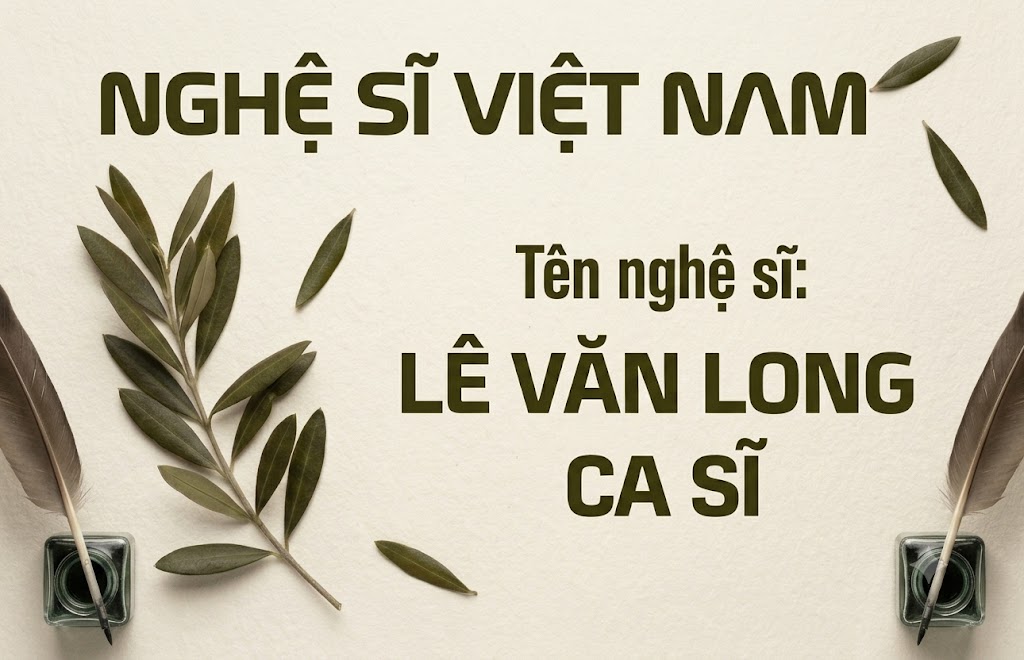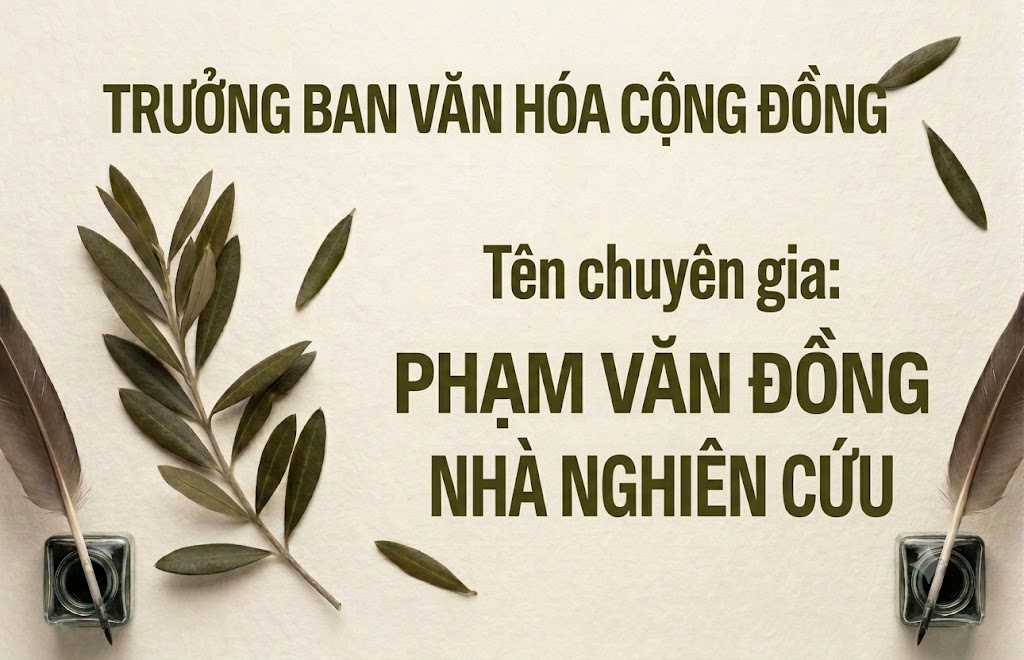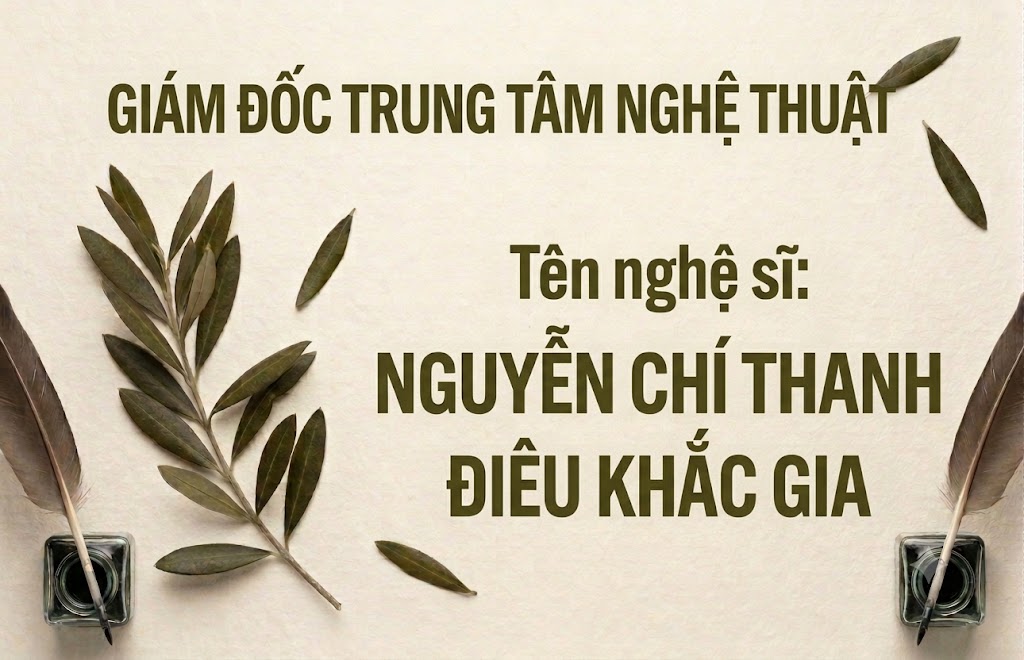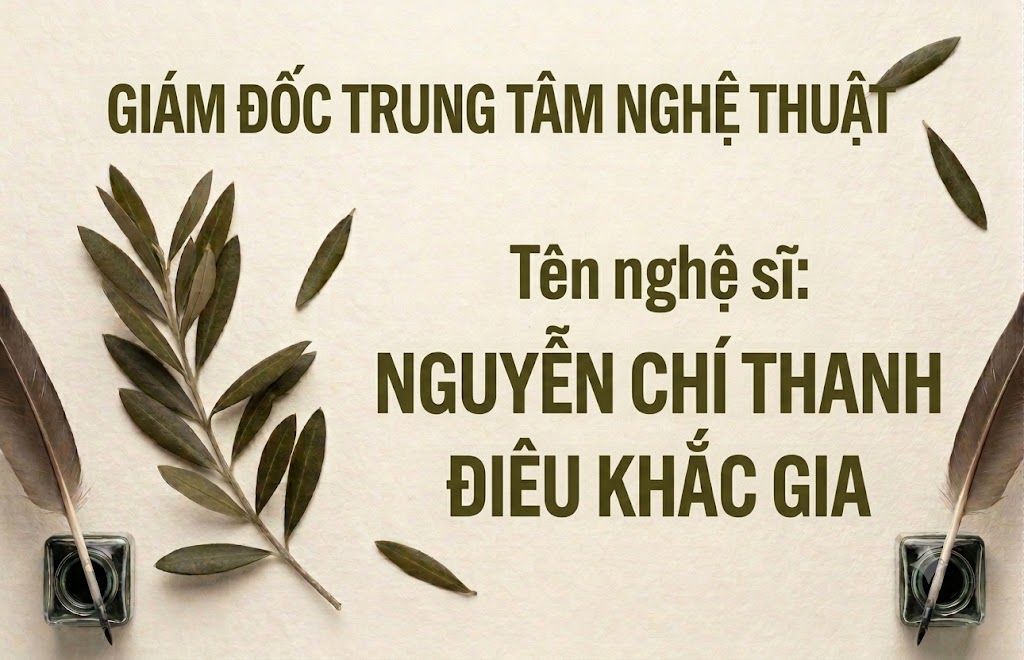
1FTV Nasi
Trong các xu hướng thiết kế đồ họa truyền thông hiện nay, việc sử dụng các phông chữ hình khối bo góc đang ngày càng được ưa chuộng rộng rãi.
Kiểu chữ này mang lại cảm giác vừa chắc chắn, hiện đại lại vừa thân thiện, không bị quá thô cứng như các dòng font vuông vắn thông thường.
Nếu bạn đang muốn tìm kiếm một giải pháp thiết kế làm tiêu đề video ngắn, banner quảng cáo hay ảnh thu nhỏ cá tính, thì font 1FTV Nasi chính là sự lựa chọn hoàn hảo.
Giới thiệu về font 1FTV Nasi
Font 1FTV Nasi là một bộ chữ display không chân phối hợp hoàn hảo giữa phong cách geometric hình học và những đường bo cong mềm mại.
Bộ font này được tối ưu hóa đồng bộ ở phiên bản 1.000, mang lại kết cấu đường nét vô cùng gọn gàng và tinh tế cho từng chữ cái.
Được thực hiện và chia sẻ rộng rãi bởi đội ngũ 1FTV, đây là giải pháp thiết kế tuyệt vời cho những ai đang tìm kiếm sự phá cách độc đáo tại Việt Nam.
Đặc điểm nổi bật của phong cách thiết kế Nasi
Sức hút lớn nhất của font 1FTV Nasi đến từ cấu trúc phom chữ vuông vắn nhưng các góc ngoài lại được bo tròn nhẹ nhàng một cách tinh tế.
Sự kết hợp này tạo ra một tổng thể thị giác vừa vững chãi, kiên cố như khối hộp, vừa mang nét mộc mạc, gần gũi và đầy tính sáng tạo.
Phông chữ được xây dựng theo định dạng all-caps viết hoa đồng bộ cho cả hai hệ thống ký tự, giúp tiêu đề luôn có sự cân bằng tuyệt đối về mặt cao độ.
Độ dày nét chữ thuộc nhóm bold vừa phải, kết hợp với các khoảng hở counter bên trong rộng rãi, giúp văn bản luôn rõ ràng và cực kỳ dễ đọc từ khoảng cách xa.
Để phông chữ vận hành mượt mà trên mọi hệ thống máy tính, phiên bản font 1FTV Nasi đã trải qua quy trình xử lý thông số kỹ thuật vô cùng kỹ lưỡng.
Hệ thống khoảng cách chữ và độ giãn dòng đã được căn chỉnh chuẩn xác, giúp các từ khi đứng cạnh nhau luôn giữ được sự liền mạch và thẩm mỹ tốt nhất.
Bên cạnh hệ thống chữ cái viết hoa đồng bộ, phông chữ còn tích hợp đầy đủ dãy số từ 0-9 cùng hệ thống các ký tự đặc biệt, dấu câu thông dụng (1234567890.:,;'"(!?)+-*/=).
Tiện ích này giúp bạn thoải mái sáng tạo các nội dung quảng cáo hay biên tập video tiếng Việt mà không lo gặp phải tình trạng lỗi hiển thị hay bị thiếu ký tự khi gõ.
Hình ảnh demo thực tế của font 1FTV Nasi
Để giúp bạn dễ dàng hình dung khả năng co giãn và hiển thị linh hoạt của phông chữ này trên các kích thước khác nhau, hãy cùng xem qua bảng mô phỏng thực tế:
Kích thước nhỏ (12pt – 24pt): Các nét chữ hình khối và dấu tiếng Việt vẫn hiển thị rõ ràng, ngay ngắn, cực kỳ dễ đọc trên màn hình điện thoại di động.
Kích thước lớn (36pt – 72pt): Đây là không gian lý tưởng để font chữ phô diễn toàn bộ sự chuyên nghiệp, tạo hiệu ứng thị giác gọn gàng cho các tiêu đề chính.
Ứng dụng của font Nasi trong thiết kế đồ họa và làm video
Sở hữu nét cá tính tối giản và cấu trúc hình học linh hoạt, font 1FTV Nasi mở ra không gian ứng dụng rộng lớn cho các dự án truyền thông:
Thiết kế thumbnail Youtube và ảnh thu nhỏ mạng xã hội: Đây là vũ khí tuyệt vời cho các video thuộc chủ đề đời sống, review ẩm thực, chia sẻ kiến thức hoặc các nội dung giải trí của giới trẻ.
Làm tiêu đề video ngắn (Tiktok, Shorts, Reels): Cấu trúc chữ độc lạ này giúp các câu từ khóa chính hay tiêu đề mở đầu video trở nên vô cùng bắt mắt và giữ chân người xem lướt chậm lại.
Banner và poster quảng cáo ngành ăn uống, sự kiện: Hoàn hảo cho các poster giới thiệu sản phẩm thức ăn, banner ngành hàng tiêu dùng hoặc poster các sự kiện giải trí năng động.
Nhận diện thương hiệu phong cách mộc mạc: Phù hợp làm logo dạng chữ khối cho các thương hiệu local brand thời trang hiện đại, tiệm cà phê, hoặc các studio sáng tạo trẻ tuổi.